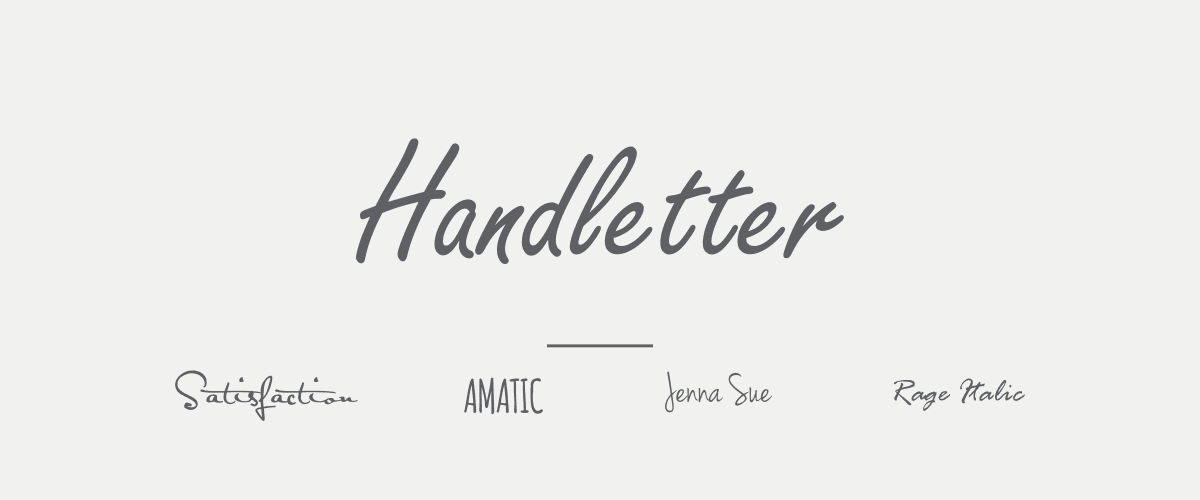
Mengenal Lebih Lanjut Tentang Tipografi Dan Jenis-jenis Font Serta Pemakaiannya
• Mengenal Pengertian Tipografi Dan Jenis-jenis Font
Tipografi merupakan ilmu memilih dan menata huruf sesuai pengaturannya pada ruang-ruang yang tersedia guna menciptakan kesan tertentu, sehingga menolong pembaca mendapatkan kenyamanan dalam membaca semaksimal mungkin.
Tipografi, seni cetak atau tata huruf adalah suatu kesenian dan teknik memilih dan menata huruf dengan pengaturan penyebarannya pada ruang yang tersedia, untuk menciptakan kesan tertentu, guna kenyamanan membaca semaksimal mungkin. – Wikipedia
Sejarah Singkat
Mengenal Pengertian Tipografi Dan Jenis-jenis Font - Sejarah Tipografi
Sejarah perkembangan tipografi dimulai dari penggunaan Pictograph. Bentuk bahasa ini antara lain dipergunakan oleh bangsa Viking Norwegia dan Indian Sioux. Di Mesir, berkembang jenis huruf Hieratia, yang terkenal dengan nama Hieroglyp pada abad sekitar 1300 SM. Bentuk tifografi akhirnya berkembang sampai di Kreta, lalu menjalar ke Yunani dan akhirnya menyebar ke seluruh eropa.
Pada perkembanganya, terjadi kurang lebih sekitar abad 8 SM di Roma, saat orang romawi mulai membentuk kekuasaannya. Karena bangsa Romawi tidak memiliki sistem tulisan sendiri, mereka mempelajari sistem tulisan Etruska yang merupakan penduduk asli Italia serta menyempurnakannya hingga terbentuk huruf-huruf Romawi saat ini, Tifografi mengalami perkembangan dari fase penciptaan dengan tangan hingga mengalami komputerisasi.
Fase komputerisasi membuat penggunaan tipografi menjadi lebih mudah dan dalam waktu yang lebih cepat dengan jenis huruf berjumlah ratusan, bahkan ribuan.
Mengapa Tipografi berperan Penting?
Peran tipografi sendiri untuk mengkomunikasikan ide atau informasi dari halaman ke pengamat. Terkadang, secara tidak sadar, kita selalu berhubungan dengan tipografi setiap hari dan setiap saat, seperti koran, majalah, labe pakaian dan contoh lainnya.
Dalam tipografi terdapat beberapa jenis huruf yang dipakai untuk tujuan dan kondisi tertentu atau yang lebih di kenal dengan nama Font. Klasifikasi huruf dibuat berdasarkan atas latar belakang sejarah perkembangan tipografi yang diambil dari momentum-momentum penting dalam perjalanan sejarah penciptan dan pengembangan bentukhuruf.
Walaupun saat ini lahir beragam jenis bentuk huruf, dunia tipografi sekarang masih banyak mengangkat jenis huruf-huruf lama, seperti Bodoni, Century, atau pun Garamond yang direproduksi serta dimodifikasi dengan teknologi digital.
Mengenal Jenis-jenis Font Serta Pemakaiannya
Mengenal Pengertian Tipografi Dan Jenis-jenis Font - Jenis Jenis Font
Dalam desain grafis secara garis besar setidaknya ada 4 jenis huruf/font utama dan dari jenis-jenis tersebut terdapat beberapa cabang jenis lain yang dikembangkan untuk memenuhi kebutuhan penggunaan. Jenis-Jenis font tersebut ialah :
1. Serif
Adalah jenis font yang memiliki ciri sirip/kaki/serif berbentuk lancip pada ujungnya. Dala tipografi disebut Counterstroke yang dipercaya dapat membubat mata lebih nyaman melihat kumpulan huruf dalam jumlah banyak serta berfungsi untuk mempermudah dalam membaca suatu kalimat. oleh sebab itu, jenis font ini paling banyak digunakan dalam buku atau artikel majalah.
Pada klasifikasi font jenis ini juga disebut Old Style karena memiliki kesan klasik, anggun, dan unik.
Mengenal Jenis-jenis Font - Serif Font
Karana nilai readibility yang baik, jenis font ini sering dijadikan judul/headline artikel karena lebih terlihat menarik jika dalam ukuran besar, namun tidak jarang juga font ini digunakan untuk isi konten misal seperti buku, artikel, majalah dan sebagainya.
Contoh dari font Serif antara lain Times New Roman, Georgia, Garamond, Cambria dan sebagainya. Ciri-ciri font Serif adalah :
• Terdapat Lengkungan Serif /Ccounterstroke
• Kontras antara tebal dan tipis garis font
• Terdapat palang / garis horizontal pada font
2. San-Serif
Jenis font San-serif merupakan kebalikan dari jenis font Serif. Kata "San" sendiri memiliki arti tanpa atau tidak. Ini berarti jenis font serif adalah jenis font yang tidak memiliki sirip/kaki/serif berbentuk lancip pada ujungnya.
Jenis huruf ini lebih tegas, bersifat fungsional dan lebih modern, biasa digunakan untuk isi konten karena lebih memberikan kenyamanan, kesain formal dan sederhana saat dibaca.
Mengenal Jenis-jenis Font - San-serif Font
Contoh font yang digolongkan San-serif adalah Helvetica, Arial, Futura, century Gothic dan lain sebagainya. Ada 3 ciri utama San-serif :
• Garis melengkung berbentuk square / persegi
• Ada perbedaankontras yang halus
• Bentuk mendekati penekanan kearah garis vertikal
3. Slab-Serif
Mengenal Jenis-jenis Font - Slab-serif Font
Juga dikenal dengan nama Egyptian, memiliki ciri kaki/sirip/serif berbentuk persegi seperti papan dengan ketebalan yang sama atau hampir sama. Memberikan kesan kokoh, kuat, solid dan stabil, lebih sering digunakan untuk header adau judul konten dan tidak cocok digunakan pada isi konten.
Beberapa contoh dari jenis font ini diantaranya : Rockwell, Courier, Claredon dan sebagainya.
4. Script
Merupakan goresan tangan yang dikerjakan dengan pena, kuas, atau pensil tajam (seperti Kaligrafi) dan biasanya miring kekanan. Dikenal juga dengan nama Handwritting, jenis font ini lebih tampak natural dan elegan seperti pada contoh dibawah ini :
Mengenal Jenis-jenis Font - Script Font
Download : Download Kumpulan 30 Font Script Terbaik Untuk Desainer Grafis
Termasuk dalam klasifikasi font script adalah Font Handletter yang dibuat seolah murni seprti tulisan tangan manusia dan bisanya digunakan untuk signature atau watermark foto, contoh terbaik dari font handletter adalah Satisfaction, Jenna Sue, Amatic dan sebagainya.
Mengenal Jenis-jenis Font - Handletter Font
Tips Memilih Tipografi Huruf dalam Dunia Desain
Untuk membuat desain yang indah dan komunikatif, tipografi tidak dapat dipisahkan dari elemen desain. ada beberapa pedoman yang bisa anda terapkan untuk memilih huruf/font yang benar diantaranya ialah :
1. Readability (Keterbacaan)
Merupakan tingkat atau level sebuah tulisan dapat difahami atau di baca dengan mudah berdasarkan kompleksitas penggunaan kata-kata dalam kalimat.
2. Clearity (Kejelasan)
Salah satu hal yang paling penting dalam memilih satu jenis font, tipografi yang baik adalah yang "menolong" orang untuk membaca, dan sebaliknya yang buruk adalah yang "mencegah" orang untuk membaca.
3. Visibility (Dapat dilihat)
Pemakaian tipe huruf harus disesuaikan dengan komposisi yang baik. peletakan huruf yang terhalang oleh gambar atau warna yang hampir sama dengan latar desain akan mempersulit orang untuk membaca.
4. legibility
Merupakan kejelasan visual dari penulisan teks, biasanya berdasarkan ukuran, jenis font, kontras, text block dan spasi antara huruf yang digunakan.